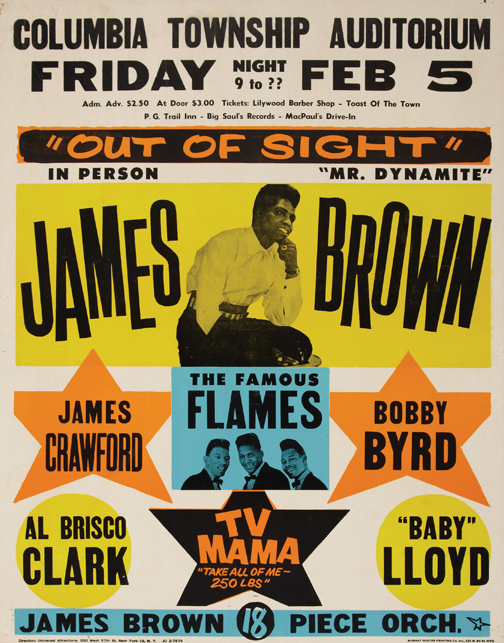
Welche Schrift passt zu Soulmusik
Ich habe ein Projekt, in welchem ich ein Musikpacket und die Werbung für eine Soul Vinyl und DVD erstellen muss.
Das ganze ist als VA gedacht, mit einem sehr edlen und anmutigen design.
Ich hatte die Idee als Tonilität ein eher Monocromes design zu wähmen, mit schwarzweissen Bidern und einer gespaltungsfarde wie z.B. ein warmes rot welches für die leidenschaft steht die die Soulkünstler in die Musik setzen.
Nun suche ich eine  Schrift mit 2-4 schnitten welche zu diesem Charakter passt.
So?
Oder so?
Oder ganz anders?
Spontan kam mir die Vinter von https://monokrom.no … weil diese wie gewünscht sehr anmutig wirkt. Für den Mengensatz in kleineren Größen könnte man dann die stärkere After Screen kombinieren. (Beide Schriften enthalten auch ein schönes Versaleszett ; )
Ob das jetzt aber »Soul« ist, kann ich nicht mit Sicherheit sagen.
Bertel trifft die Kernfrage: Soll man damit eher Blue Note oder Motown assoziieren? Welche Interpreten und Jahrgänge? Wenn du "edel" schreibst, dann wohl eher Blue Note, oder? Da geht dann mit Sicherheit was schickes serifenloses, aber wenn die Gestaltung stimmig ist, könnte es genausogut auch mit Helvetica, Univers oder Microgramma funktionieren ...
Naja schwirig zu sagen, es darf schon eine Blues note haben, aber hauptsächlich sollte man schon eine Schrift finden die zu Soul passt.
Die Interpreten weiss ich leider noch nicht, aber es wird aufjedenfall Soul aus dem 50-80er sein, das steht fest.
Ich persönlich finde die Vinter schon sehr schön, weiss aber nicht ob das so ganz passt.
@bertel: keine von den von dir gezeigten beispielen.
Die helvetica könnte schon gehen, blos wirkt das dann warscheinlich zu "gewönlich" ;(
Etwas Leichtes einer Interpretation der amerikanischen Grotesk vielleicht?!
50er -- 80er ist ja schon sehr weit auseinander. Guck dir doch mal Alben der Epochen an. Dann siehst du evtl. in welche Richtung es gehen soll, oder, was ganz und gar nicht in Frage kommt. Soul ist so ein weites Feld, da kann man nicht sagen: »Nimm die oder die Schrift!«  :neenee:
Ja da hast du recht, ich suche mal n paar alben durch... Ich weiss, es gibt nie "die Universele Schrift für irgendetwas"
Andere Frage: Kennt Ihr eine Serifenfont, welche nur leicht betonte serifen hat, welche aber einen weichen charakter hat. Sie soll nicht zu kantig sein
Etwas richtung Optima.
Ich hab immer geguckt aus welcher Zeit und aus welcher Gegend die Musik ist. Das heisst nicht, dass die Schrift aus dem selben Jahrzehnt stammen sollte, aber dass sie Menschen geläufig ist, die dazumal musikinteressiert waren.
Die „Soul-Schrift“ gibt es meines Erachtens nicht. Ich tendiere aber zu so was amerikanischem wie der Knockout, die sich auf Holzlettern bezieht wie sie auf den typischen Tourplakaten der 50er und 60er, vor allem farbiger Künstler zu sehen sind. Aber Soul kann ja auch 70er, 80er und 90er sein - dann muss man ganz anders rangehen…
Fertigo?